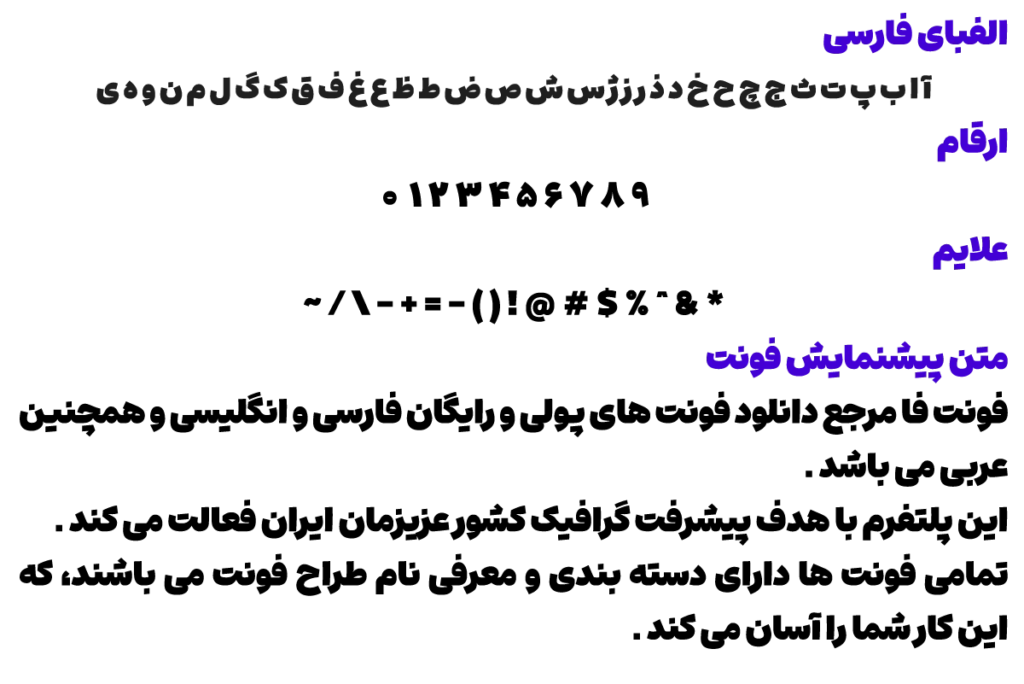
پیشنمایش فونت استعداد مَد
فونت فارسی استعداد مَد - Estedad Mad
توضیحات و معرفی فونت استعداد مَد
فونت فارسی استعداد مَد ( Estedad Mad ) از مجموعه فونت های آزاد می باشد، همچنین نوع فونت عنوان می باشد.
فونت فوق العاده زیبای معرفی شده توسط محمد درویشی در سال 1403 طراحی و ساخته شده است.
استعداد مَد یک فونت مخصوص تیترها و عنوان‌هاست که بر اساس فونت استعداد طراحی شده است.
تایپ فیس مربوطه ضخیم‌تر از فونت استعداد است و ویژگی‌هایی در آن پیاده‌سازی شده تا بتواند در تیترها بدرخشد و توجه‌ها را به خود جلب کند.
همچنین فونت استعداد مَد در یک وزن پر رنگ است.
تصویر شعر کهن وطنم نوشته شده با تایپ‌فیس استعداد مد